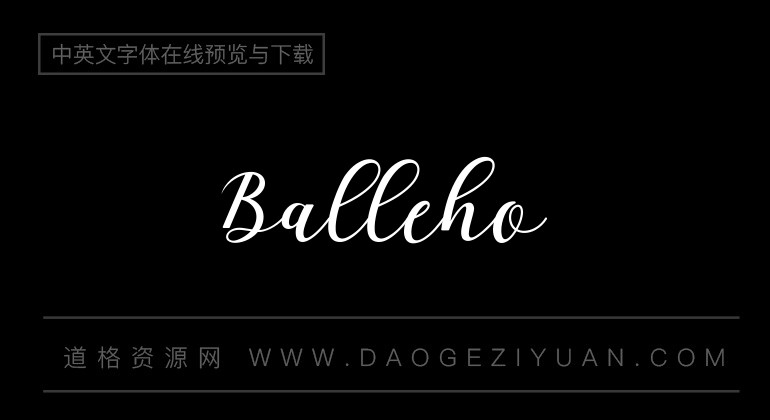
Balleho
Balleho 字体是一款简洁、优雅的英文字体,由荷兰设计师Pieter van Rosmalen设计。它灵感来自古老的荷兰文字,具有优雅的外观和细节,以及完美的线条和曲线。它可以用于各种不同的环境,从海报到网页,从文字到图片,都可以使用它。Balleho字体可以增强文字的可读性,并且可以使文字看起来更加优雅,更具有艺术感。
Balleho是一款非常不错的手写艺术字体,具有很好的视觉感,适合于文化类的宣传设计、商业类品牌的广告和产品包装设计以及个性化文字排版等较多场景。